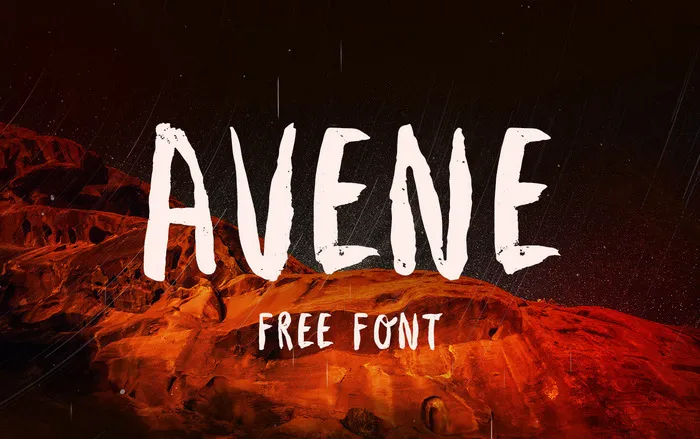
Avene Brush Font – Download Grátis
Através do designer Gatis Vilaks, chegamos a uma novidade para o seu arsenal de fontes — Avene Brush Font. Introduzido pela KRISIJANIS MEZULIS, esta é uma fonte brush livre e completamente disponível, perfeita para adicionar à sua coleção de recursos gráficos. Com um design feito a mão com o uso de uma ferramenta de pincel muito grossa, Avene Brush Font oferece uma aparência visual única e impecável. Se você busca algo que traga vida e personalidade ao seu design, este é exatamente o que você precisa. As 94 unidades de caracteres presentes nesta fonte permitem maior versatilidade. Para quem busca adicionar um toque único ao seu projeto, Avene Brush Font não se apresenta apenas como uma opção. Suportando todos os gílios básicos e equipado com o que você precisa para criar textos elegantes e sofisticados, esta fonte é perfeita para qualquer designer. O download inclui um arquivo .otf e outro em formato .woff — duas formas populares de utilizar essa bela fonte. Com Avene Brush Font na sua coleção, certamente você encontrará uma maneira única de adicionar a personalidade que seu projeto merece.